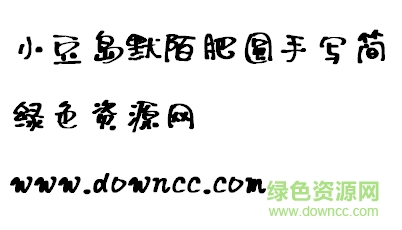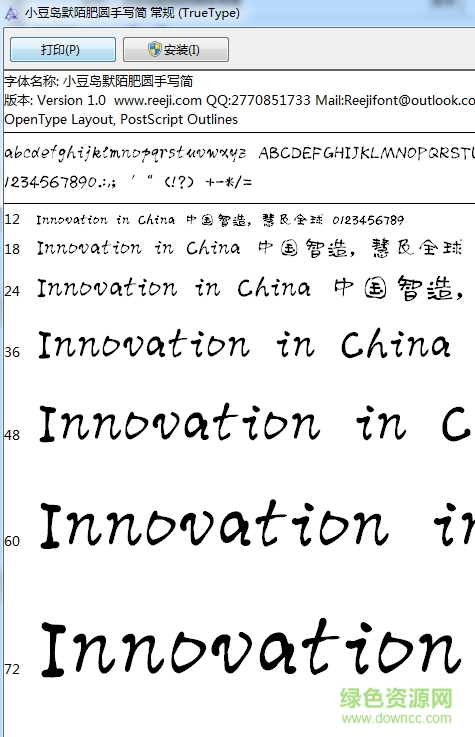
小豆島默陌肥圓手寫(xiě)簡(jiǎn)是一款令人賞心悅目的手寫(xiě)字體,字體粗細(xì)相間,形如流水,整體有著無(wú)拘無(wú)束的韻味,更多好看的字體歡迎到綠色資源網(wǎng)下載!
小豆島默陌肥圓手寫(xiě)簡(jiǎn)字體家族系列主要提供常規(guī)等字體風(fēng)格樣式,該字體尾部的甩尾有力且有豐富的筆觸細(xì)節(jié),大字效果突出且引人注目;并且最大程度還原作者書(shū)寫(xiě)字形,細(xì)節(jié)表現(xiàn)完整,且字庫(kù)完整,可以廣泛應(yīng)用于名片設(shè)計(jì)、新聞媒體、宣傳海報(bào)、ppt、影視制作以及內(nèi)容用字等領(lǐng)域。
小豆島默陌肥圓手寫(xiě)簡(jiǎn)字體是類(lèi)似于草書(shū)的手寫(xiě)藝術(shù)字體,打造不同尋常的特色書(shū)法,讓你的平面設(shè)計(jì)與眾不同,每一個(gè)字體都有不一樣的藝術(shù)魅力!